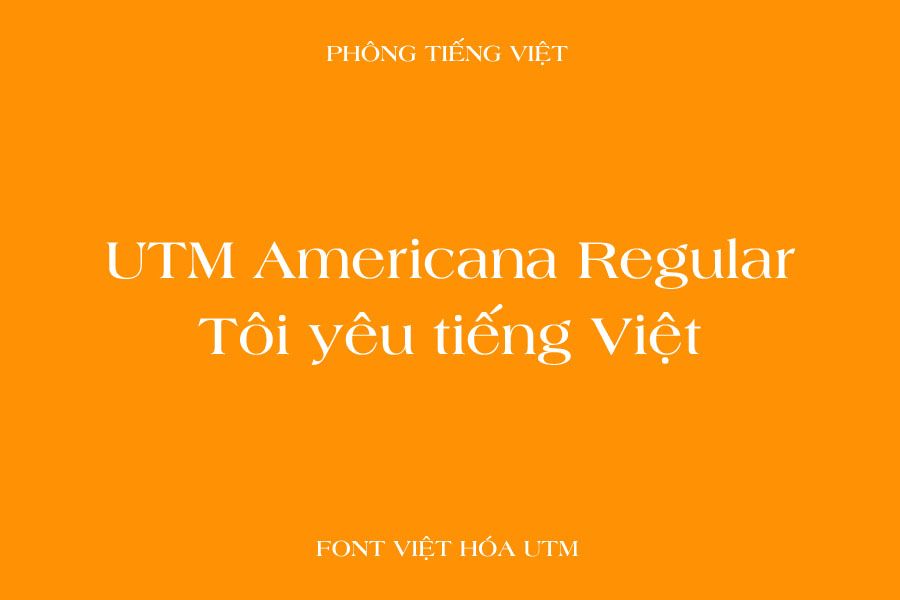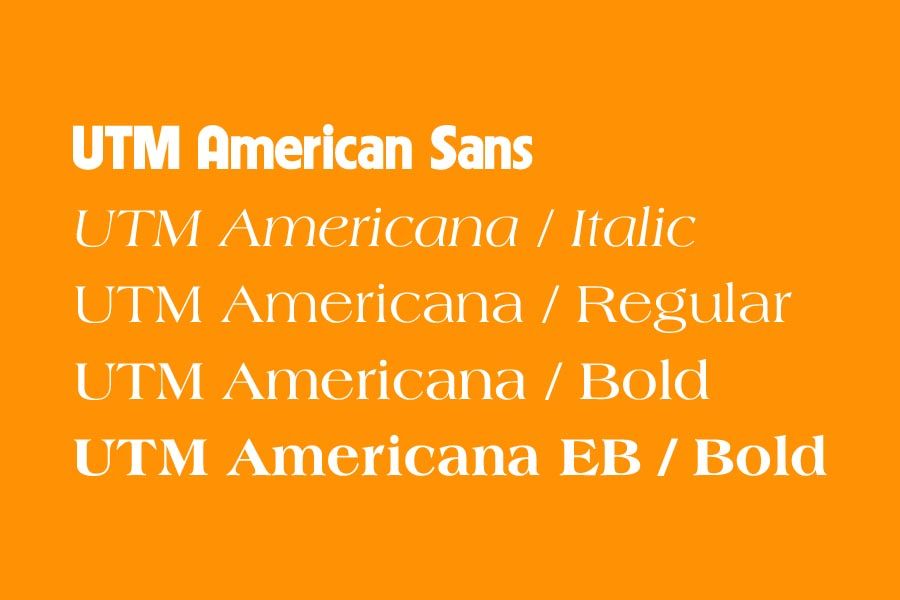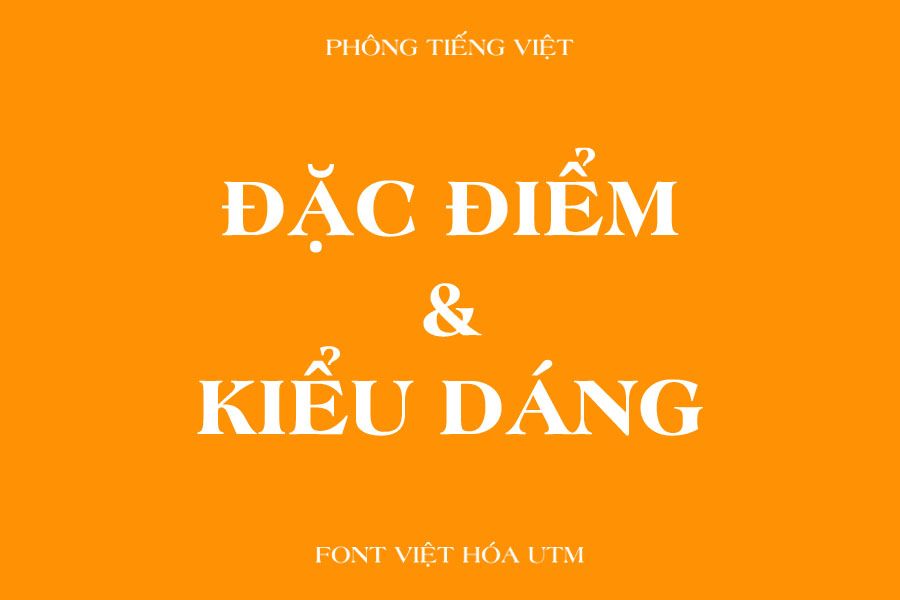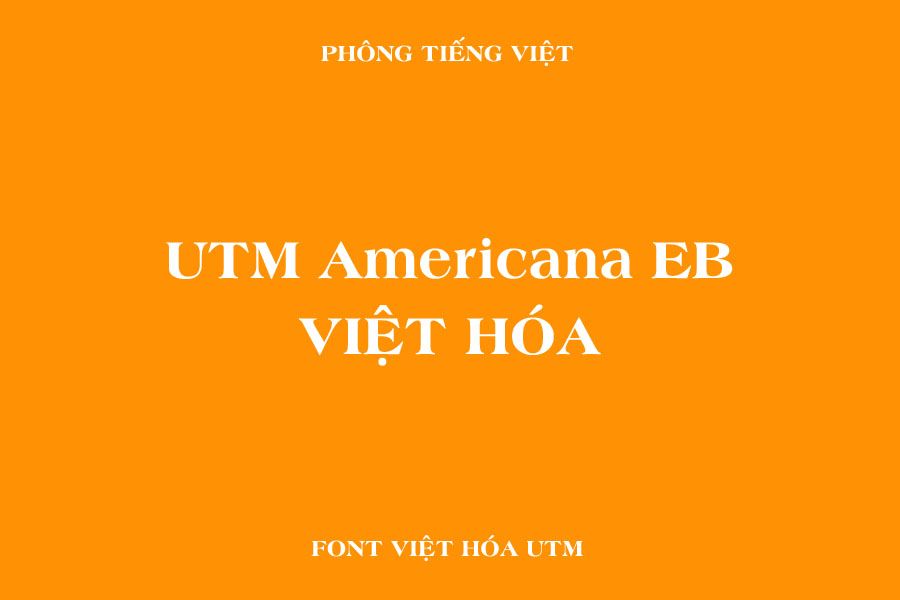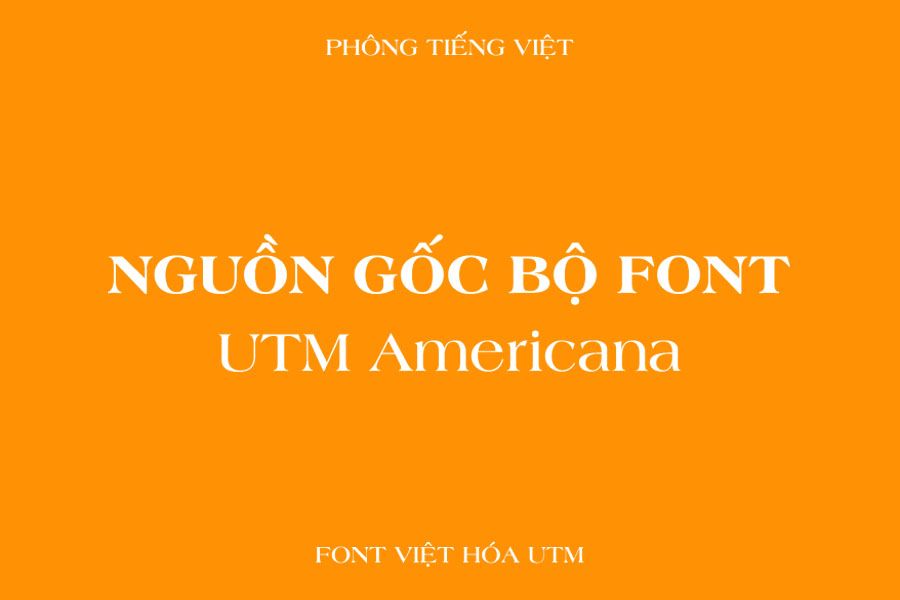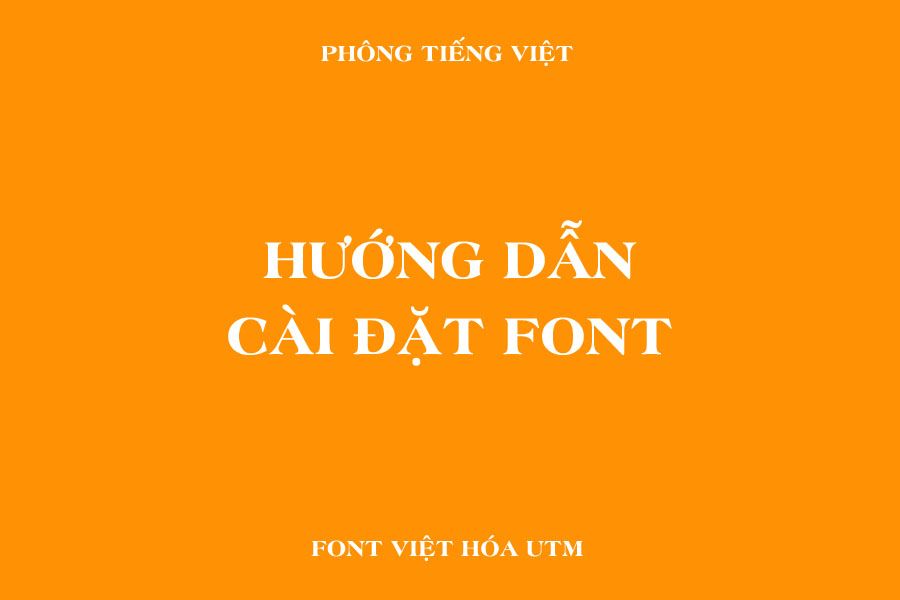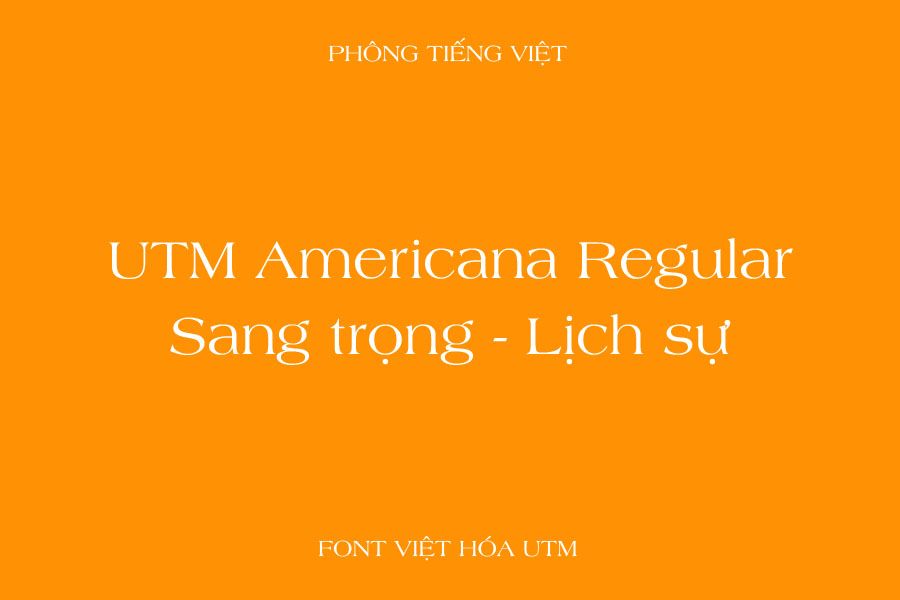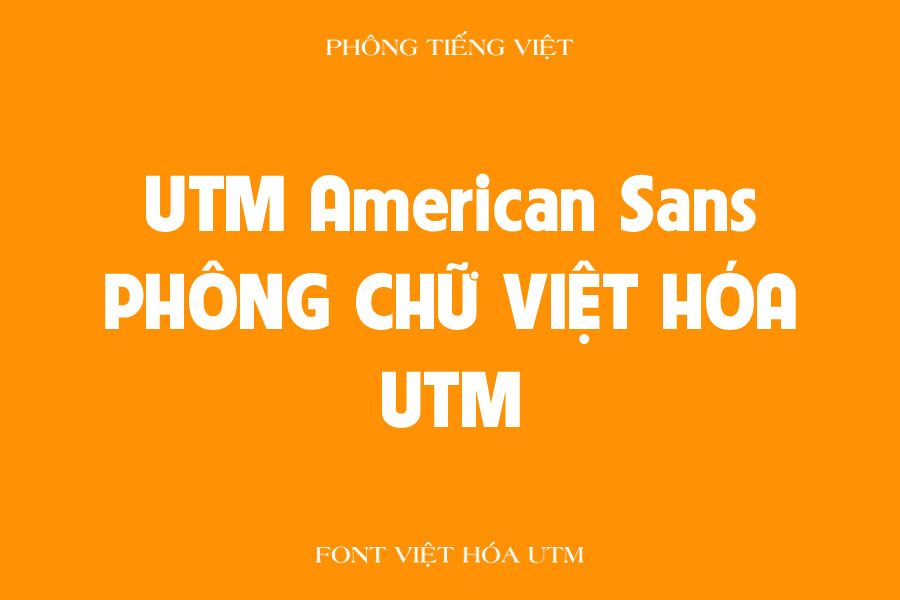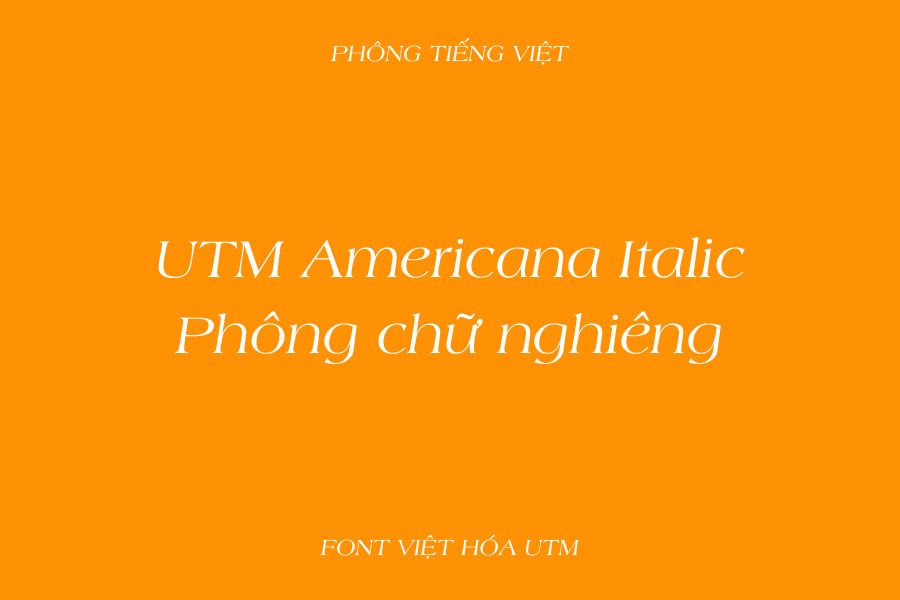
Font chữ UTM American là một trong những kiểu chữ Việt hóa được yêu thích nhất hiện nay, đặc biệt trong thiết kế mang phong cách học đường, báo chí cổ điển hay retro. Không chỉ sở hữu vẻ ngoài đơn giản, rõ ràng, bộ font còn đem lại cảm giác hoài niệm, nghiêm túc và trang trọng – rất phù hợp với các dự án cần sự chuẩn mực và dễ đọc.
Bộ font này thực chất không chỉ có một mà bao gồm 5 kiểu chữ biến thể mang tính ứng dụng cao: sans-serif hiện đại, serif cổ điển, extra bold trang trọng và italic mềm mại. Tất cả đều được Việt hóa tỉ mỉ, hỗ trợ đầy đủ tiếng Việt, phù hợp với nhiều nhu cầu thiết kế khác nhau.
Font UTM American được phát triển dựa trên cảm hứng từ các kiểu chữ sans-serif và serif cổ điển của Mỹ, gắn liền với văn hóa học đường, báo chí và tài liệu in ấn học thuật. "UTM" là viết tắt của Unicode Thiên Minh – dự án Việt hóa font được biết đến rộng rãi tại Việt Nam từ đầu thập kỷ 2010.
Phiên bản Việt hóa do Đinh Kiên thực hiện, được đánh giá cao nhờ khả năng hiển thị tiếng Việt rõ ràng, không lỗi dấu, chuẩn Unicode. Đây là một trong những bộ font có độ hoàn thiện cao nhất trong hệ thống font học đường – cổ điển.
Dù bao gồm nhiều biến thể, bộ font UTM American có một số đặc điểm nổi bật chung:
1. Đường nét rõ ràng, cấu trúc gọn gàng, phù hợp cả màn hình lẫn in ấn
2. Khoảng cách ký tự vừa phải, dễ đọc và dễ căn chỉnh
3. Chữ viết hoa nổi bật, giúp tiêu đề bắt mắt hơn
4. Hỗ trợ Unicode tiếng Việt đầy đủ: bao gồm tất cả dấu và ký tự tiếng Việt
Mỗi kiểu chữ trong bộ sẽ có nét cá tính riêng, từ nghiêm túc đến mềm mại, từ mạnh mẽ đến cổ điển.
Bộ font UTM American bao gồm tổng cộng 5 kiểu chữ biến thể – mỗi kiểu mang một cá tính riêng biệt, phục vụ đa dạng mục đích thiết kế từ tiêu đề mạnh mẽ đến văn bản mềm mại, từ poster cổ động đến tài liệu học thuật trang trọng.
Font sans-serif với độ dày cao, rõ ràng và mạnh mẽ. Phù hợp cho thiết kế tiêu đề, bảng hiệu, poster cổ động, hoặc infographic cần sự rõ ràng, trực tiếp và tác động thị giác mạnh.
Dạng nghiêng của font serif, tạo cảm giác mềm mại và nghệ thuật. Thường dùng cho trích dẫn, lời dẫn, đoạn văn cảm xúc hoặc thiết kế mang tính lãng mạn.
Biến thể cơ bản nhất trong nhóm serif – chữ có chân, nét mảnh và dễ đọc. Phù hợp với sách in, tài liệu học thuật, tạp chí, hoặc các thiết kế mang tính truyền thống.
Giữ được vẻ cổ điển nhưng tạo nhấn mạnh bằng nét đậm. Thường dùng làm tiêu đề phụ, đoạn nổi bật, hoặc phần cần tách biệt trong văn bản dài.
Phiên bản đậm nhất của họ font Americana serif. Dùng để tạo tiêu đề chính, bìa sách, banner in ấn hoặc các thiết kế mang thông điệp mạnh mẽ, cổ điển nhưng không lỗi thời.
Bộ font chữ UTM American không chỉ đơn thuần là một font sans-serif Việt hóa. Đây là một hệ font đầy đủ, bao gồm 5 biến thể phong cách khác nhau, giúp bạn linh hoạt ứng dụng trong mọi dự án thiết kế: từ áp phích cổ động, tiêu đề website, sách báo học thuật đến slide thuyết trình chuyên nghiệp.
Dễ dùng, đẹp, hỗ trợ tiếng Việt đầy đủ và tương thích trên mọi nền tảng – bộ UTM American xứng đáng là lựa chọn không thể thiếu cho bất kỳ ai đang tìm kiếm một bộ font đa dụng và đáng tin cậy.